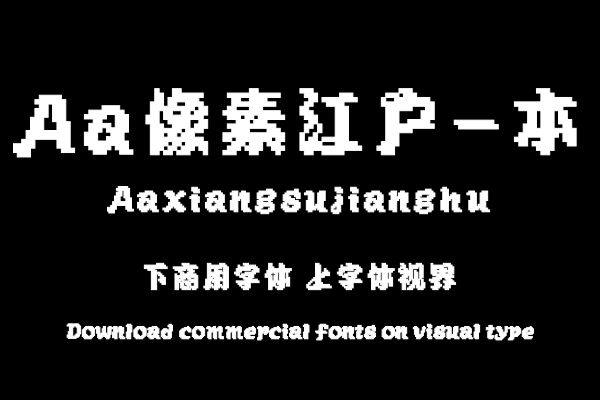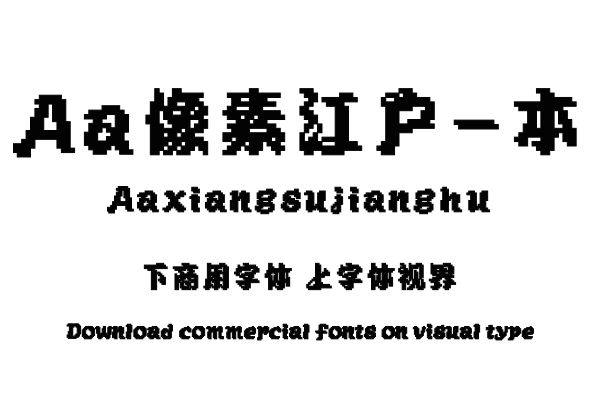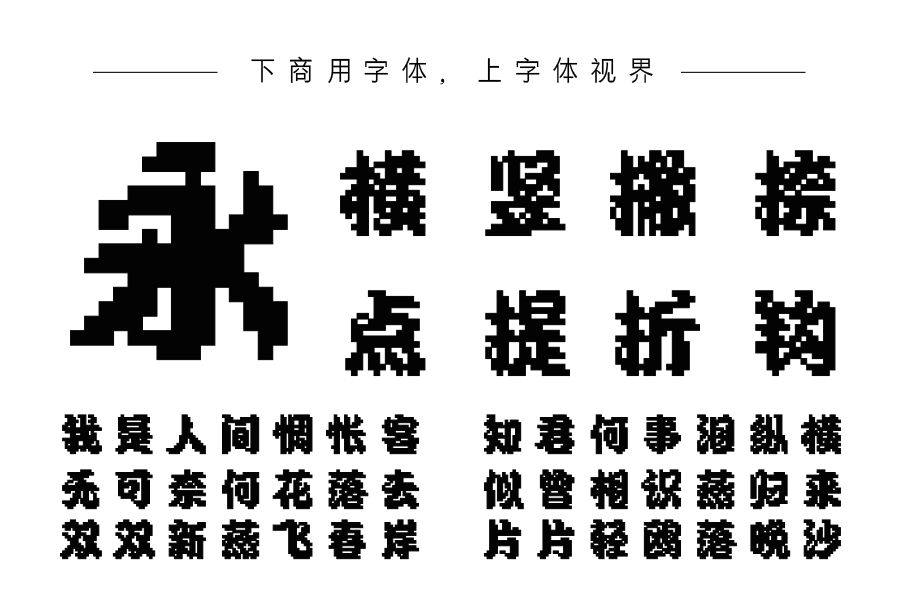
基于江户招牌字体衍生的一款点阵字体,在16×16的像素面积制作,延续了勘亭流字体的大字重、饱满字面、横笔画的倾斜动势和笔画动态连带。字体风格既有毛笔书写带来的随......购买须知:“下载服务费”与“字体VIP”所获得字体 仅用于个人非商用, 商用请联系付费授权。本字体为电脑用字,手机没有root权限不支持直接手机换字(手机如何root,请自行百度搜索教程)。购买前请先 了解清楚后再付款 ,字体为虚拟产品无法回收 一旦购买不支持退款。